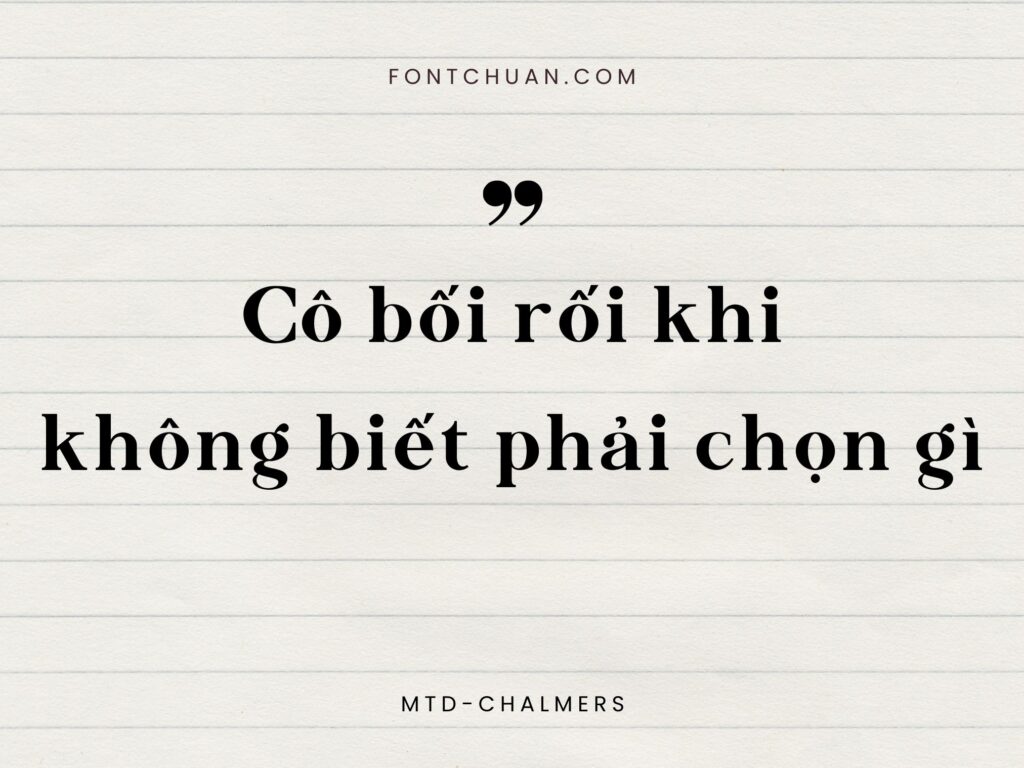
Font MTD Chalmers là một kiểu chữ serif cổ điển hiện đại, được thiết kế bởi Swisthink Std và đã được Việt hóa bởi Mộc Hạ. Font này hỗ trợ đầy đủ tiếng Việt cùng hơn 90 ngôn ngữ khác, mở rộng khả năng ứng dụng trong các thiết kế đa ngôn ngữ. Đây là một trong những phông chữ được cộng đồng thiết kế đánh giá cao và sử dụng trong nhiều dự án sáng tạo, đáp ứng nhu cầu đa dạng của người dùng.
MTD Chalmers nổi bật với các đường nét thanh lịch và tinh tế, tạo cảm giác sang trọng và chuyên nghiệp. Font rất phù hợp cho các thiết kế logo, tiêu đề, bao bì sản phẩm, thiệp mời và các ấn phẩm đòi hỏi sự trang nhã và độc đáo. Các ngành nghề phù hợp bao gồm quảng cáo, giáo dục và công nghệ. Font này cũng lý tưởng cho các sự kiện như Tết, Giáng sinh, Valentine và các lễ hội khác.